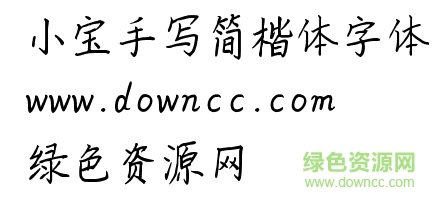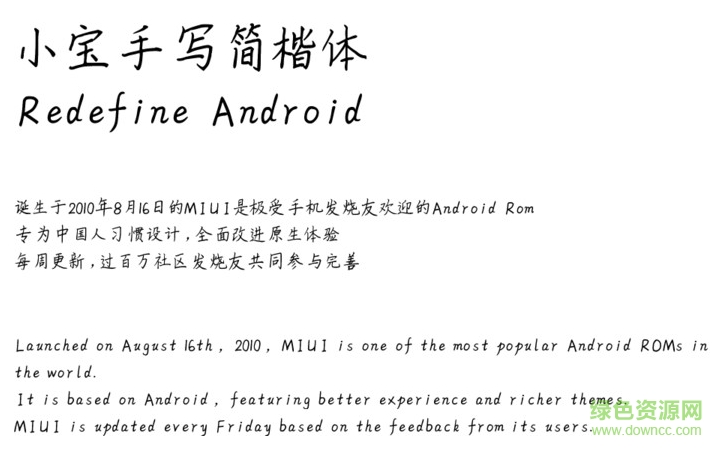
小寶手寫簡楷體字體
小寶手寫簡楷體是小米商店全新上線的手寫字體,采用楷體模板制作,造型簡潔字跡清晰,給人舒適的視覺體驗和閱讀美感,歡迎大家來綠色資源網(wǎng)下載使用!
小寶手寫簡楷體字體介紹
純手寫字體,給您不一樣的感覺。換一種字體換一種心情!本字庫是在國家標準簡體字庫GB2312所包含6763漢字的基礎(chǔ)上,又增加了近200常用字,已經(jīng)覆蓋了大陸99.75%的漢字使用頻率,足以滿足日常需求。
小寶手寫簡楷體
手寫體說明
手寫體概念:手寫體是一種使用硬筆或者軟筆純手工寫出的文字,手寫體文字代表了中國漢字文化的精髓。這種手寫體文字,大小不一、形態(tài)各異,在計算機字庫中很難實現(xiàn)錯落有致的效果。只能使用手工寫字的方法傳承下去。
手寫體文字制作步驟:手寫體文字是用“美工筆”在紙上寫出來的,可能一個字會寫幾十遍或者更多,之后再從中間選出寫的比較可以接受的拍照,上傳到電腦上用photoshop處理后制作而成。